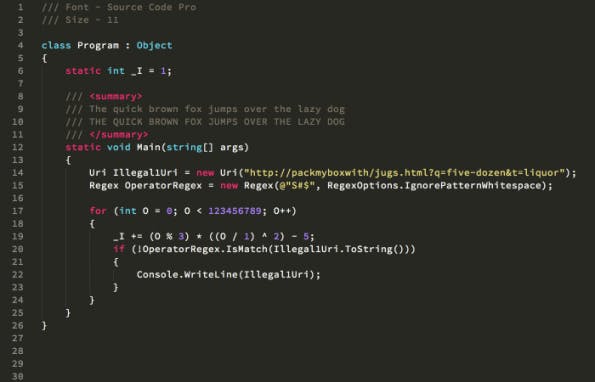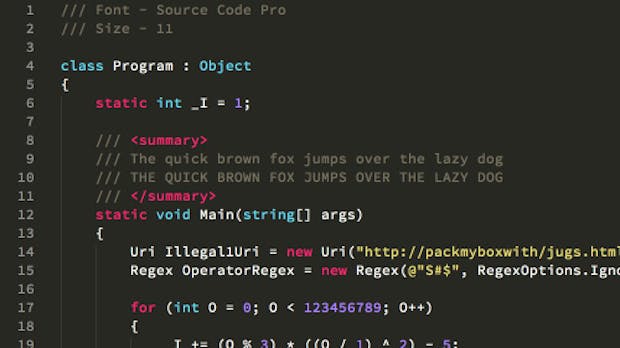
Schicker Code: Die besten Fonts zum Programmieren
Für Menschen, die den Großteil ihres Tages vor einem Monitor sitzen, gibt es heutzutage eine Menge zu optimieren: Sitzhöhe, Anstellwinkel der Rückenlehne oder auch Neigung und Höhe des Bildschirms. Was leider oft untergeht, ist die Tatsache, dass Wohlbefinden am Arbeitsplatz auch durch Software beeinflusst werden kann. Gerade Entwickler starren oft stundenlang auf Quellcode und vergessen dabei, dass die Wahl einer optimalen Schriftart für mehr Übersichtlichkeit und Konzentration am Arbeitsplatz sorgen kann.
Umfrage auf Slant.co
Auf der Stimmungsplattform Slant haben sich etliche Entwickler ausgetauscht und für ihre favorisierten Schriftarten zur Darstellung von Quelltext abgestimmt. Die fünf Schriftarten mit der besten Bewertung stellen wir hier vor:
Beim Arbeiten mit Quellcode sollte man auf gute Lesbarkeit, und damit auch auf eine gute Schriftart achten. (Screenshot: Slant.co)
- Source Code Pro: Die meisten Entwickler sind von dem kostenlosen Open-Source-Font „Source Code Pro“ von Adobe überzeugt. Sie verfügt über sechs verschiedene Schriftschnitte und ist von der beliebten „Source Sans“ abgeleitet. Im Gegensatz zum Vorbild handelt es sich allerdings um einen Monospace-Font (das heißt, jedes Zeichen verfügt über die gleiche Breite) für mehr Übersichtlichkeit.
Adobe Source Code Pro (Screenshot: Slant.co)
- Consolas: Die Schrift ist seit Windows Vista im Lieferumfang von Windows enthalten, man kann jedoch auch kostenlos heruntergeladen werden, um sie auf einem Mac verwenden. Consolas ist ebenfalls eine Monospace-Schriftart und verwendet Microsofts ClearType für die Kantenglättung.
Consolas (Screenshot: Slant.co)
- Inconsolata-g: Hierbei handelt es sich um eine Modifikation der kostenlosen „Inconsolata“. Hier wurden allerdings einige Zeichen verändert, um Quellcode deutlicher darstellen zu können. Beispielsweise wurden die Kursivierung der Anführungszeichen und die Trennbarkeit von „l“ und „1“ verbessert.
Inconsolata-g (Screenshot: Slant.co)
Wenn euch von den hier vorgestellten Schritften keine gefällt, dann sind die restlichen Beispiele auf Slant ebenfalls definitiv einen Blick wert!
Hoppla, nicht „monospace“ mit der Foundry „Monotype“ verwechseln ;) Ich benutze auch Source Code Pro und bin damit sehr glücklich. Interessant, wie schnell sich dieser Font verbreitet hat, ist er doch noch recht jung.